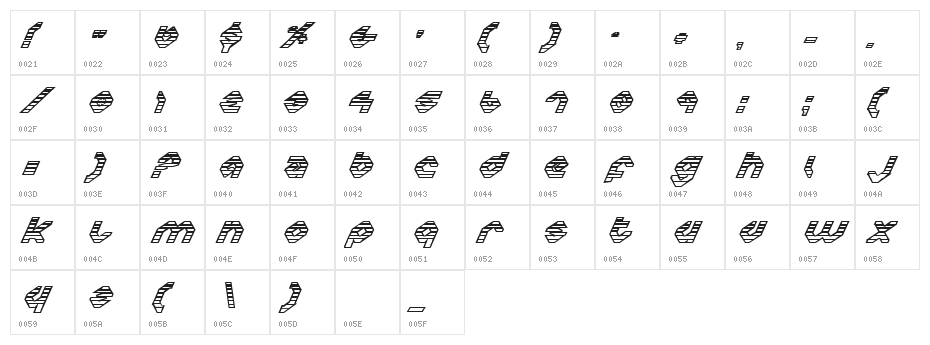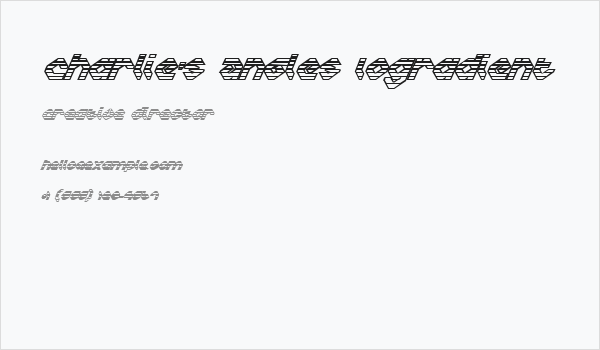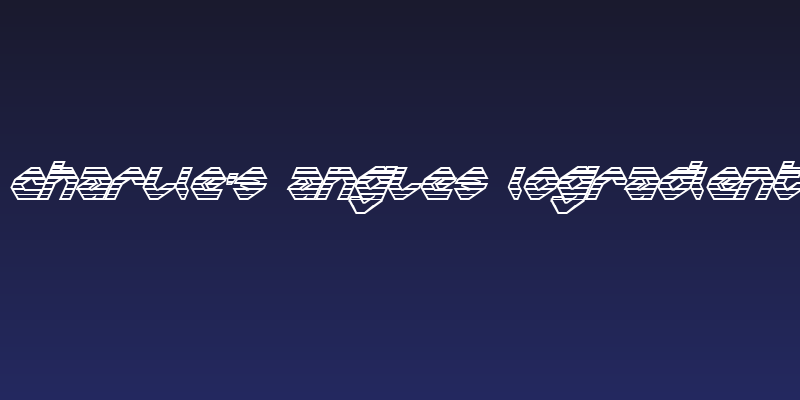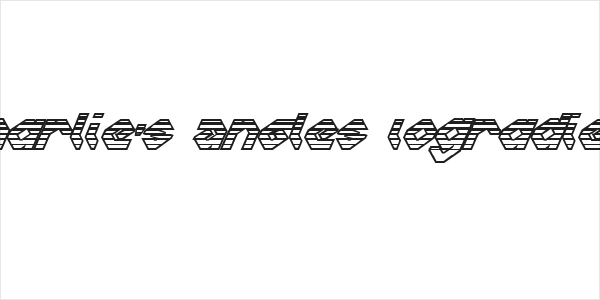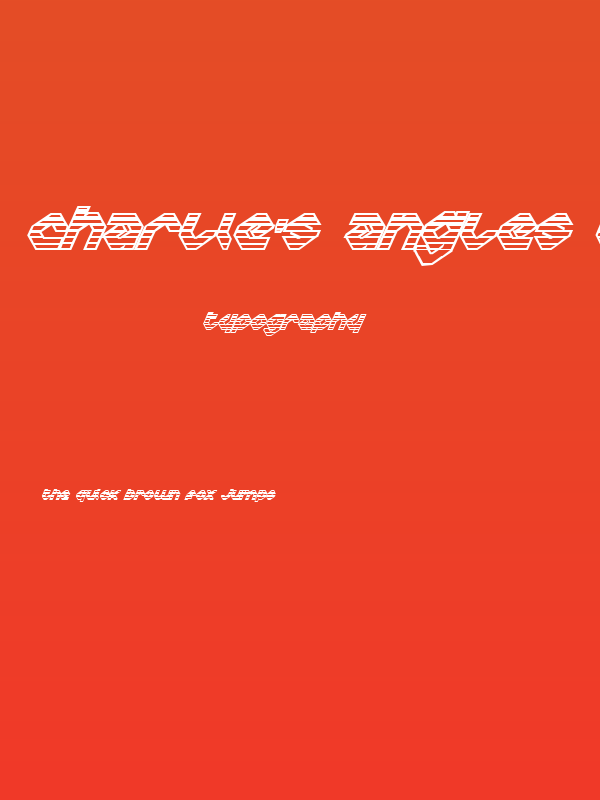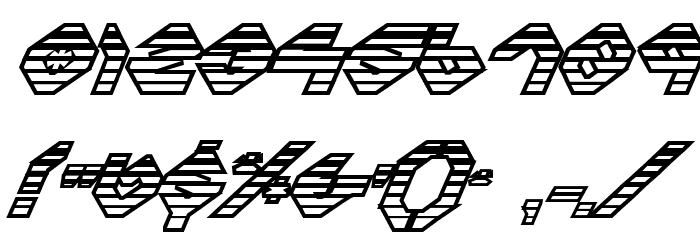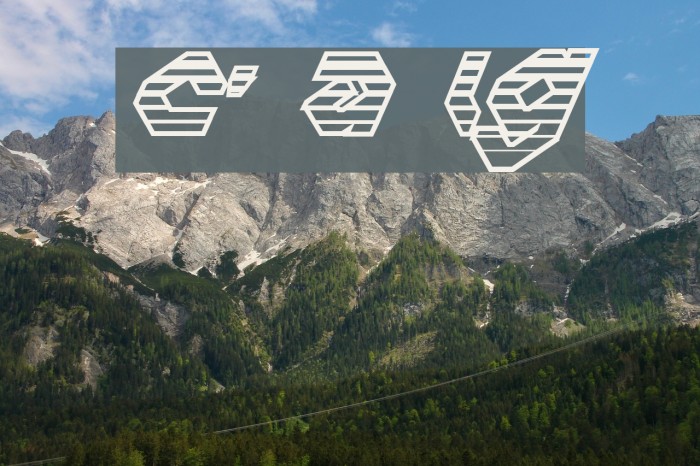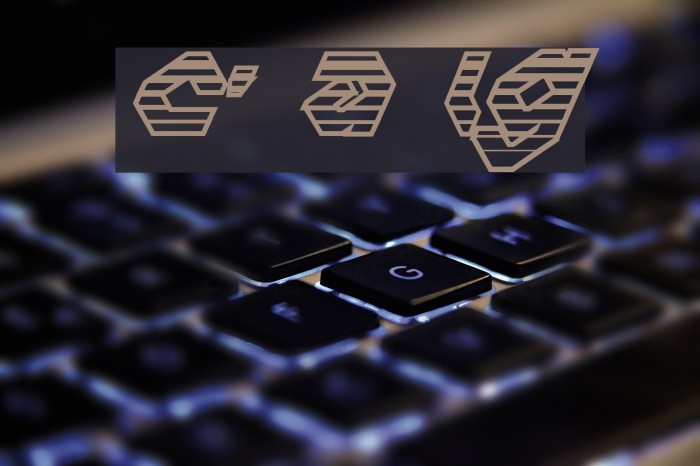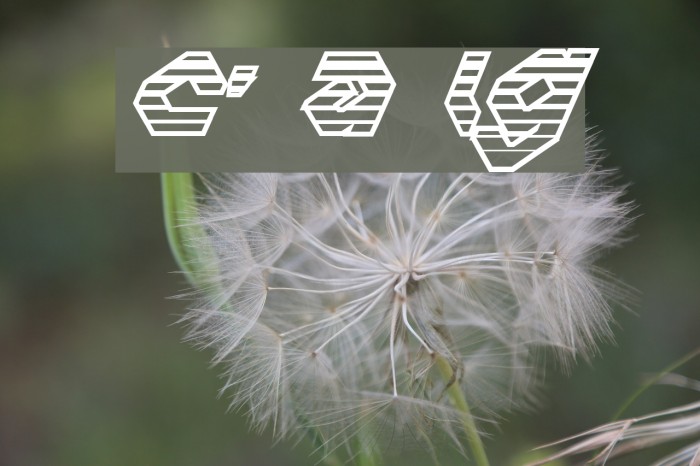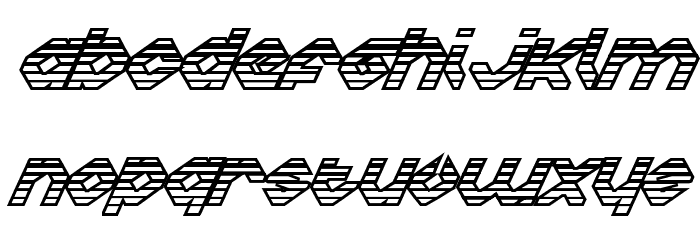
Charlie's Angles IoGradient Font
| Projets proposés | Ideal for branding, posters, album covers, and digital art projects that require a modern and eye-catching design. |